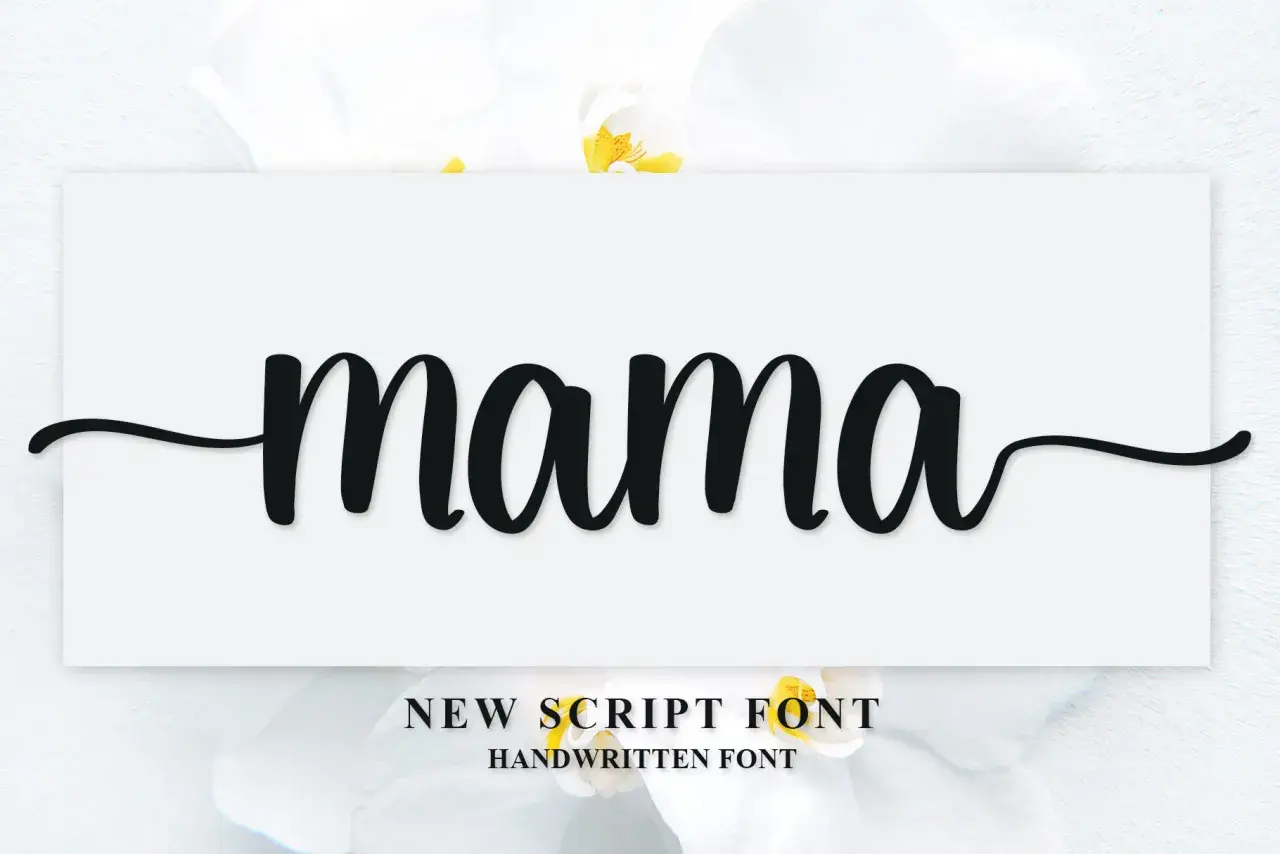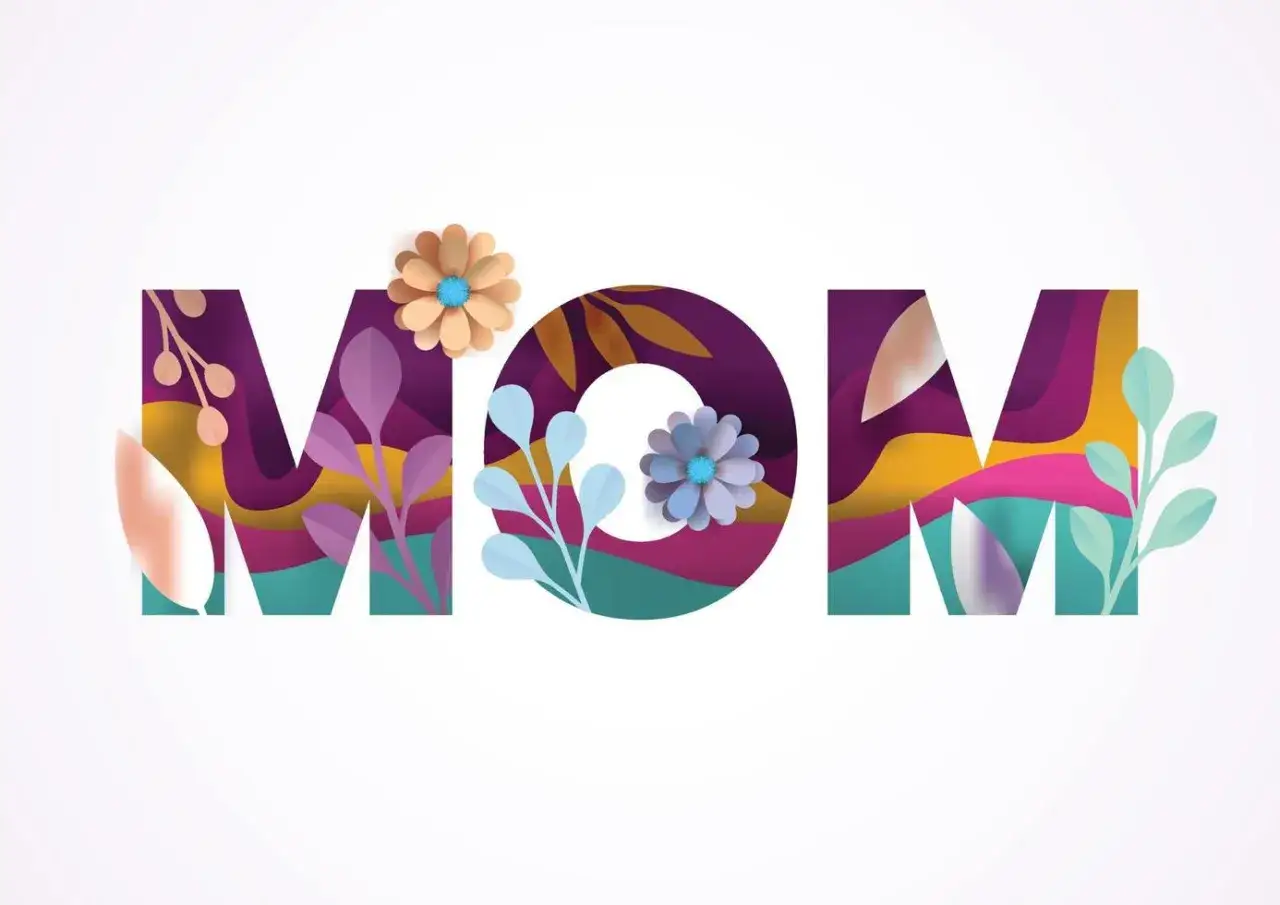
Cómo elegir la tipografía para diseñar la palabra mamá
La palabra "mama" escrita en una fuente script elegante, sobre un fondo blanco con flores de orquídea.
La palabra mamá tiene una carga emocional enorme, y en tipografía eso importa casi tanto como el dibujo de cada letra. Si la pieza está bien resuelta, la palabra transmite cercanía; si está mal compuesta, se vuelve pesada, cursi o simplemente difícil de leer. Aquí verás cómo interpretar su forma, qué familias tipográficas funcionan mejor, cómo construir una composición equilibrada y qué errores conviene evitar en tarjetas, láminas y regalos personalizados.
Lo esencial para diseñar la palabra mamá con buen criterio
• La tilde importa: “mamá” es la forma correcta cuando hablamos de la madre y cambia tanto la lectura como el ritmo visual.
• Las tipografías manuscritas funcionan, pero solo si hay suficiente contraste y espacio entre trazos.
• Para piezas serias o premium, una serif elegante suele dar mejor resultado que una fuente recargada.
• La combinación más segura suele ser una palabra protagonista y un texto secundario limpio.
• Antes de publicar o imprimir, conviene revisar legibilidad, kerning, tamaño real y soporte final.
La tilde define sentido y también ritmo visual
En español, la RAE recoge mamá como la forma general culta para “madre”; la forma llana mama persiste en usos populares y rurales, pero en diseño conviene no dejar margen a la duda. Esa tilde pequeña hace dos cosas a la vez: aclara el significado y crea un gesto ascendente que equilibra la palabra cuando la trabajas en una composición.
Yo siempre la miro como parte del dibujo, no como un trámite ortográfico. Si la palabra va sola, la tilde puede convertirse en un punto de tensión visual; si está rodeada de más texto, ayuda a marcar jerarquía y a evitar que la pieza se vea plana. Por eso, antes de pensar en adornos, conviene decidir si el mensaje quiere sonar íntimo, elegante, infantil o contemporáneo; a partir de ahí, todo lo demás encaja mejor.
Con esa base, la elección de la familia tipográfica deja de ser decorativa y pasa a ser una decisión de tono.
Las letras
Las familias tipográficas que mejor la favorecen
Para esta palabra, no busco solo una fuente “bonita”. Busco una familia que soporte emoción sin sacrificar lectura, porque en una tarjeta o una lámina el ojo necesita entender el mensaje en un segundo.
Familia Qué transmite Cuándo la usaría Riesgo habitual
Script caligráfica, como Dancing Script, Great Vibes o Parisienne Cercanía, celebración, gesto manuscrito Tarjetas, láminas pequeñas, packaging emocional Perder legibilidad si se reduce demasiado
Sans geométrica, como Montserrat, Poppins o Quicksand Limpieza, modernidad, calma visual Piezas contemporáneas, fondos con textura o florales Puede resultar fría si ocupa toda la composición
Serif elegante, como Cormorant Garamond, EB Garamond o Playfair Display Delicadeza, valor editorial, sensación premium Láminas decorativas, carteles, regalos de interior Se debilita en tamaños muy pequeños o fondos recargados
Brush casual, como Pacifico, Just Another Hand o Alex Brush Espontaneidad, tono artesanal, energía amable Mensajes cortos, stickers, firmas, detalles de marca Exagera el tono si se usa para frases largas
Display personalizada Identidad fuerte y carácter propio Campañas, piezas únicas, diseños con una sola palabra protagonista Exige mucho control de espaciado y contraste
Las familias citadas están disponibles en Google Fonts, así que probar combinaciones es sencillo y no obliga a comprometerse desde el inicio con una licencia cerrada. Mi fórmula más segura sigue siendo la misma: una fuente protagonista para la palabra y una sans limpia para el resto. Si la protagonista ya tiene mucha personalidad, el texto secundario debe hacer de apoyo, no competir.
Cuando la familia elegida ya encaja con el tono, el siguiente paso es componer la pieza para que esa emoción no se pierda por exceso de adornos.
Cómo construir una composición que no se pase de dulce
La composición es donde una buena idea se salva o se rompe. Yo suelo revisar cuatro cosas antes de darla por buena:
• Jerarquía: decido si la palabra mamá es el centro absoluto o si comparte escena con una dedicatoria breve.
• Kerning: ajusto el espacio entre pares como M-A o M-Á, porque el ojo nota enseguida cuando una letra queda pegada o demasiado abierta.
• Respiración: dejo aire alrededor. En una tarjeta pequeña de 10 x 15 cm me funciona que la palabra principal ocupe entre un tercio y la mitad del ancho, no más si hay florituras.
• Tamaño real: en pantalla no bajaría la palabra principal de 28 px si la fuente tiene trazos finos; en impresión, para una tarjeta A6, me muevo con frecuencia entre 24 y 36 pt según el grosor y la función.
Kerning es el ajuste óptico entre letras; tracking, el espacio global de un bloque. Esa diferencia parece técnica, pero en una pieza emocional cambia mucho: un buen kerning hace que la palabra se lea como un gesto, no como una cadena de caracteres. Si además el fondo es limpio y el color acompaña, la lectura mejora sin necesidad de añadir más ornamento.